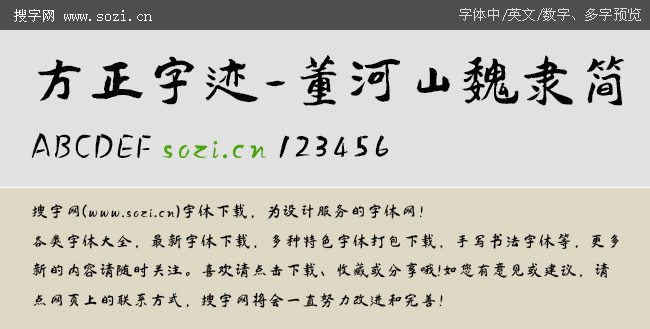
方正字跡-董河山魏隸簡
搜字網(wǎng)提供一款方正字跡-董河山魏隸簡中文字體下載,字體風格介于魏碑與漢隸的交界體,字形基本上承襲漢隸,但在結構上有一定變化,其特點是較漢隸方嚴規(guī)整其字體結構優(yōu)美,風格獨特,藝術個性鮮明,雅俗共賞,廣泛用于各種書刊、畫冊的設計印刷中,字體具有強烈的視覺沖擊力,是報紙和雜志和書籍中常用字體, 應用于海報、個性促進品牌標志設計、字體設計等領域。